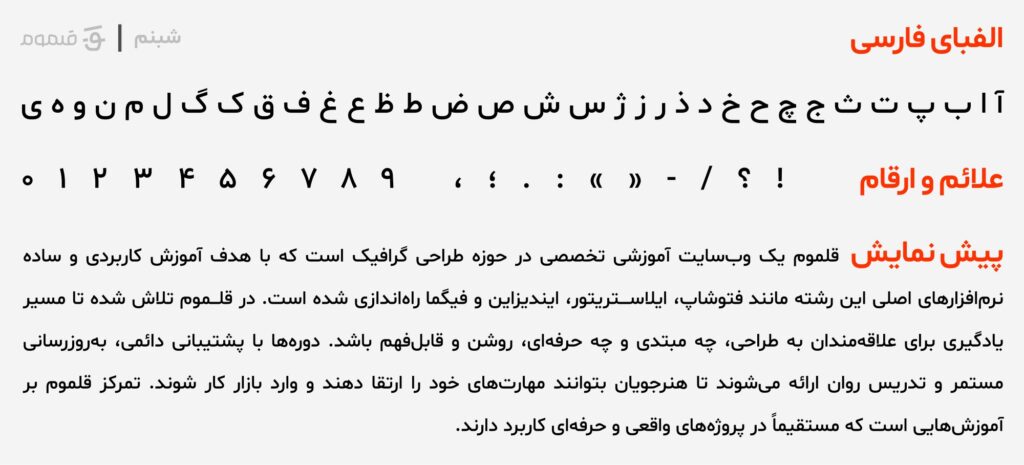
فونت شبنم با طراحی باز و دوستانهاش، برای محیطهای کاربرپسند و پروژههایی که به یک حس صمیمی نیاز دارند بسیار مناسب است. این فونت در ۳ وزن عرضه شده و به خاطر فاصله مناسب بین حروف، خوانایی بالایی در اندازههای مختلف دارد.
شبنم معمولاً در وبسایتهای محتوایی، رابط کاربری نرمافزارها و حتی متون چاپی سبک استفاده میشود. این فونت نیز رایگان و متنباز بوده و توسعهدهندگان میتوانند بدون دغدغه از آن در پروژههای تجاری خود استفاده کنند. از همین رو فونت شبنم را میتوان یکی از بهترین فونتهای فارسی رایگان دانست.